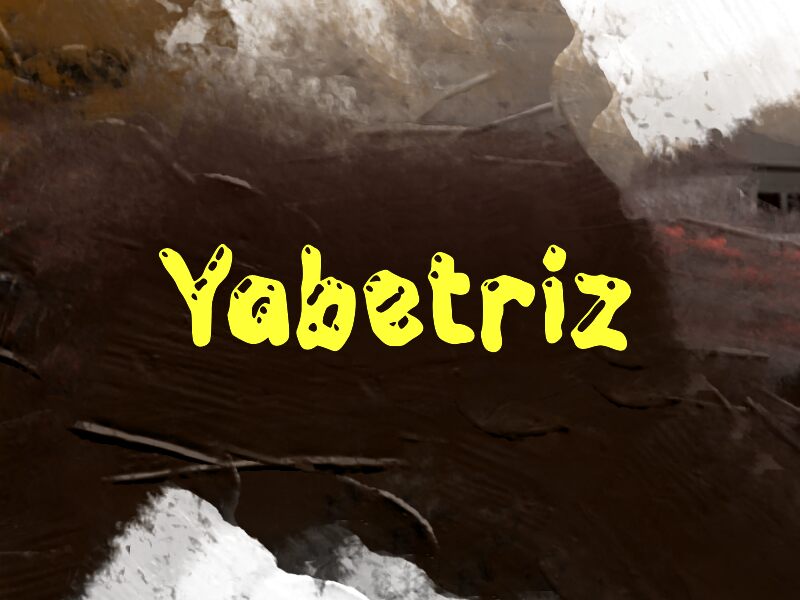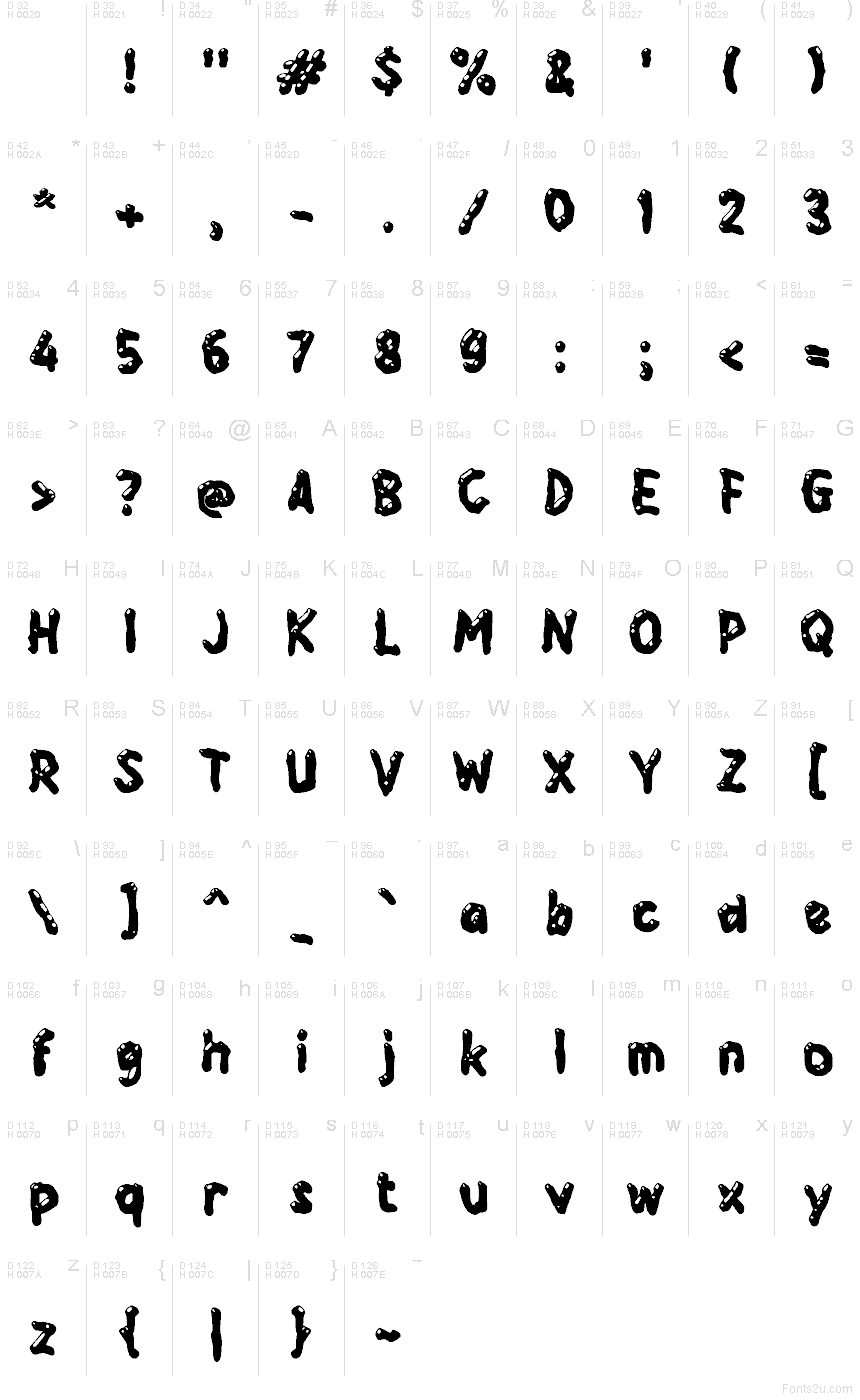
Yabetriz
Yabetriz, da wep, é uma fonte display estilo cartoon gratuita que parece feita de gotas pretas brilhantes, com formas arredondadas que parecem inchar, ceder e dobrar-se como se as letras fossem de borracha macia. Os reflexos brancos repetidos e as bordas irregulares conferem ao design um efeito saltitante e desenhado à mão; o seu caráter advém mais da superfície e da silhueta do que de qualquer sistema geométrico rigoroso.
Esta textura fluida e animada faz todo o sentido em cartazes infantis, embalagens de snacks, títulos de BD, convites de festas e miniaturas de YouTube, onde a letra precisa de atuar como um elemento gráfico. Funciona especialmente bem em títulos curtos, ideal para quando pretende um visual divertido e elástico que realce uma marca lúdica ou anime os seus conteúdos para as redes sociais.